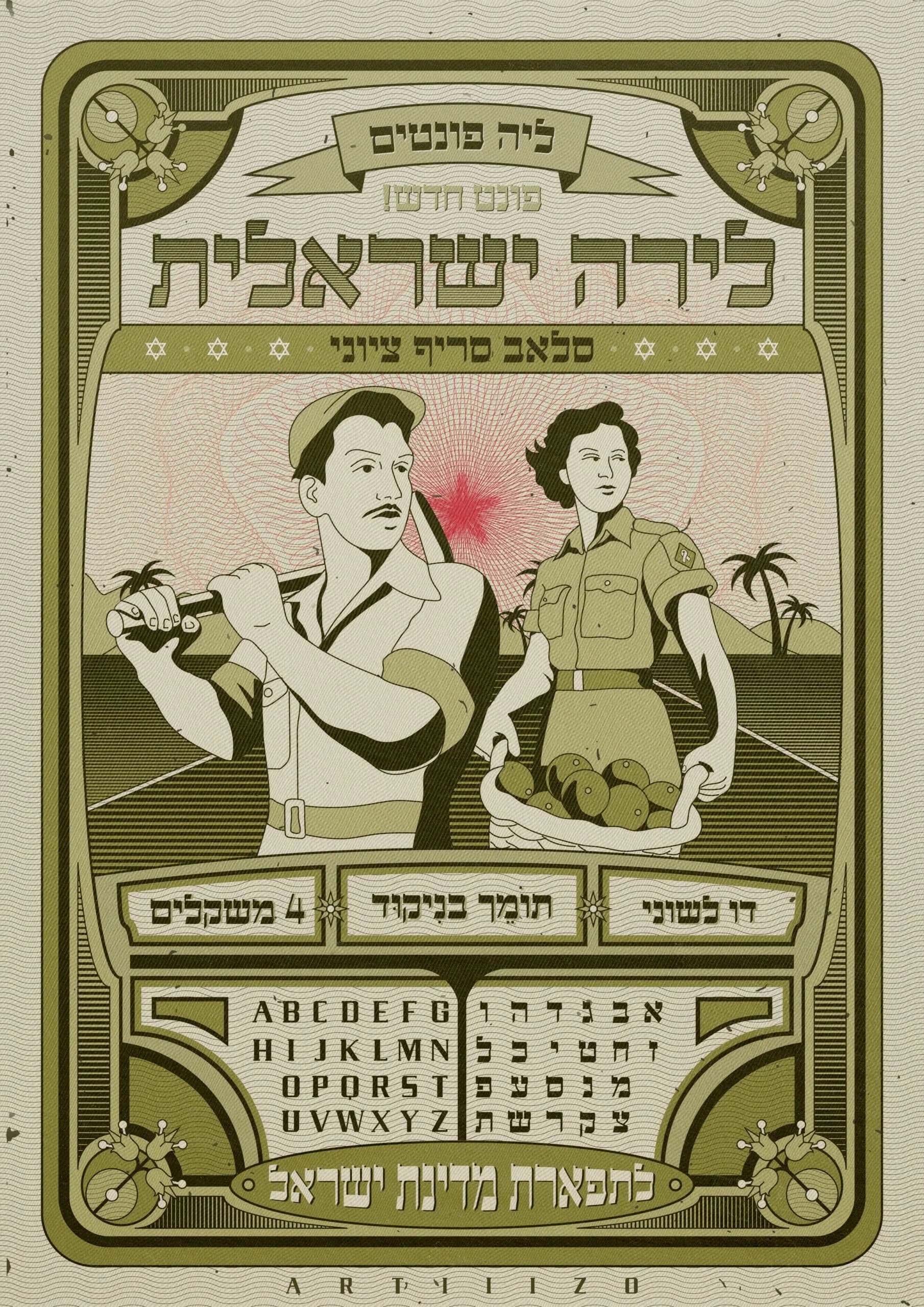
לירה ישראלית – פונט עם שורשים היסטוריים ונוכחות מודרנית - פונט לירה ישראלית הוא עיצוב מחודש, עדכני ומדויק של הפונט ההיסטורי ששימש בשטרות הלירה הישראלית בימיה הראשונים של המדינה. הפונט המקורי שידר יציבות, אמינות ורשמיות – ערכים שאנו שמרנו עליהם גם בעיצוב הפונט החדש. הפונט מעביר תחושה של ישראליות אותנטית, רטרו וביטחון. הוא מתאים למיתוג, עיצוב כרזות, שלטים, ספרים היסטוריים, תערוכות ומוצרים. האותיות העבות והגיאומטריות מעניקות לפונט כוח, בהירות וקריאות גבוהה בכותרות. הוא משלב תחושת נוסטלגיה עם נגיעה מודרנית – שילוב בין עבר להווה, בדיוק כמו הסיפור של הפונט הזה. לירה ישראלית מתאים במיוחד למיתוג וזהות חזותית של עסקים עם אופי ישראלי, עיצוב כרזות ושלטים למוסדות, מוזיאונים ופרויקטים היסטוריים, ספרים, מגזינים ופרסומים רשמיים, הדפסים על מוצרים, מרצ'נדייז וחולצות, ועיצוב כותרות לעיתונות ופרויקטים ממשלתיים. עם לירה ישראלית, כל פרויקט מקבל נופך של היסטוריה, יציבות וסגנון שלא ניתן להתעלם ממנו. לייט רגיל סמי בולד אקסטרה בולד נסו אותי | רישיון בחירת אפשרותדסקטופווב משקל בחירת אפשרותלייטרגילסמי בולדאקסטרה בולדמשפחהנקה כמות של פונט לירה ישראלית הוספה לסל לחצו למאמר המלא עיצוב פוסטר: studio artiiizo